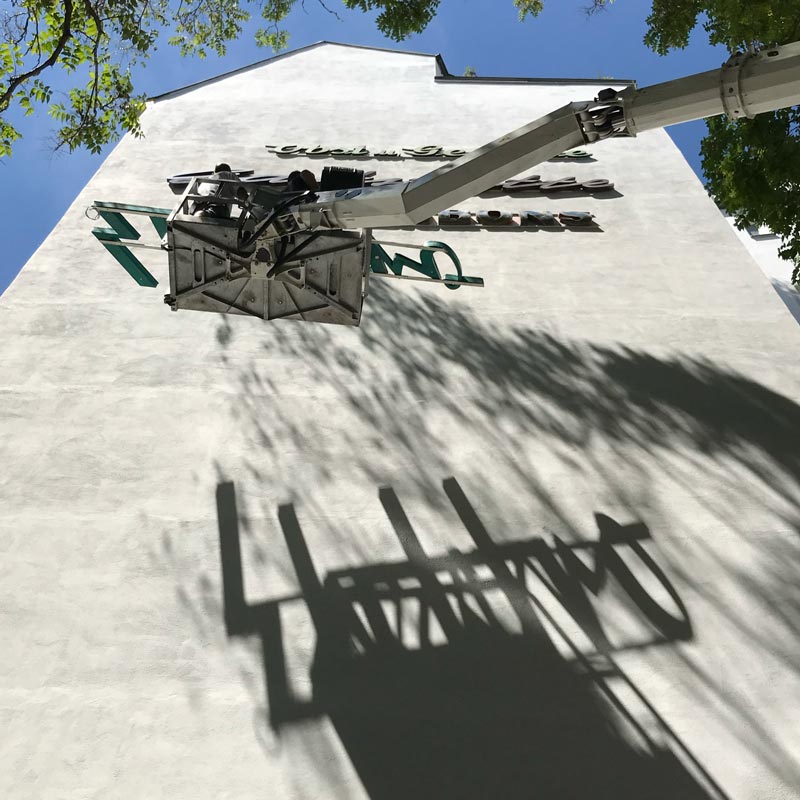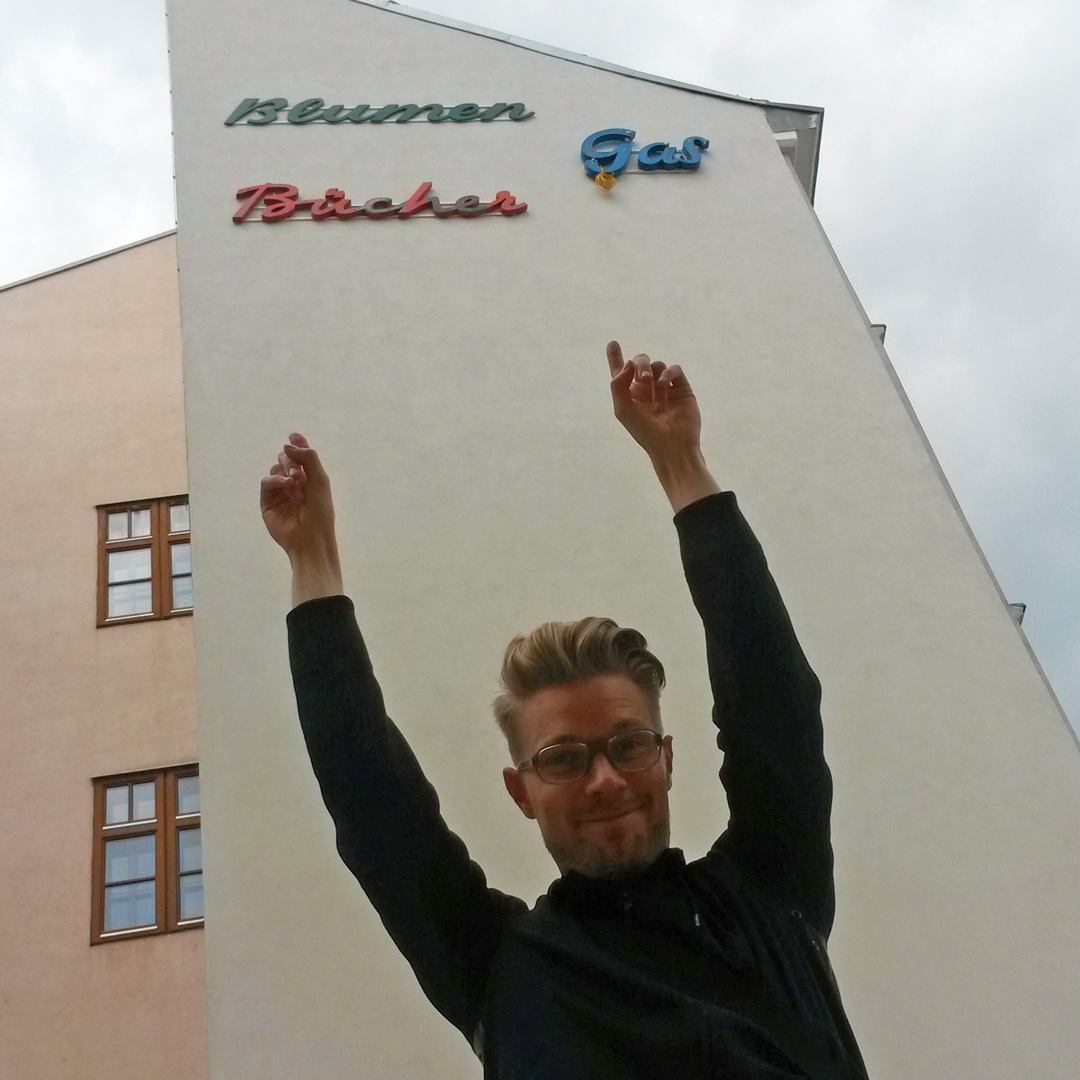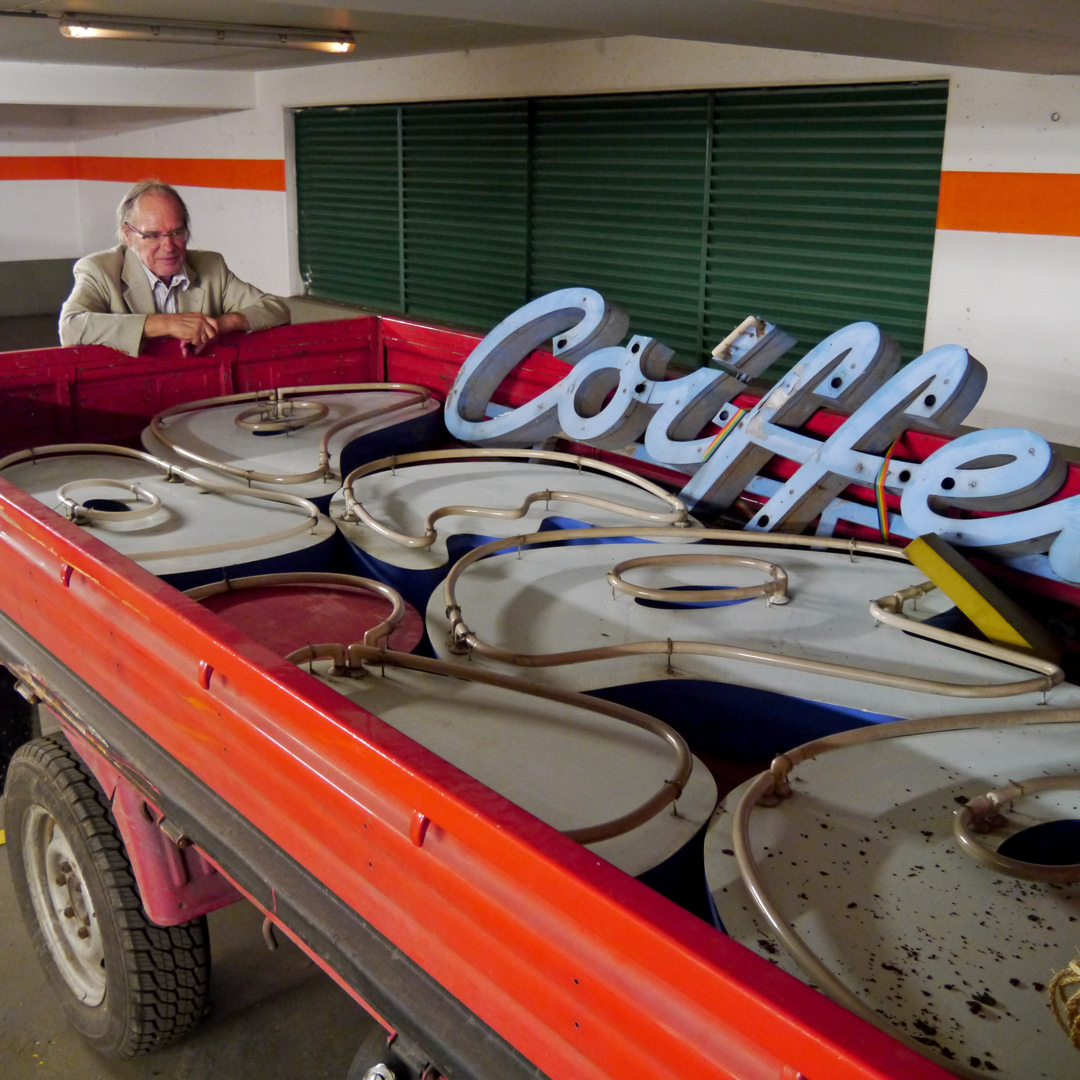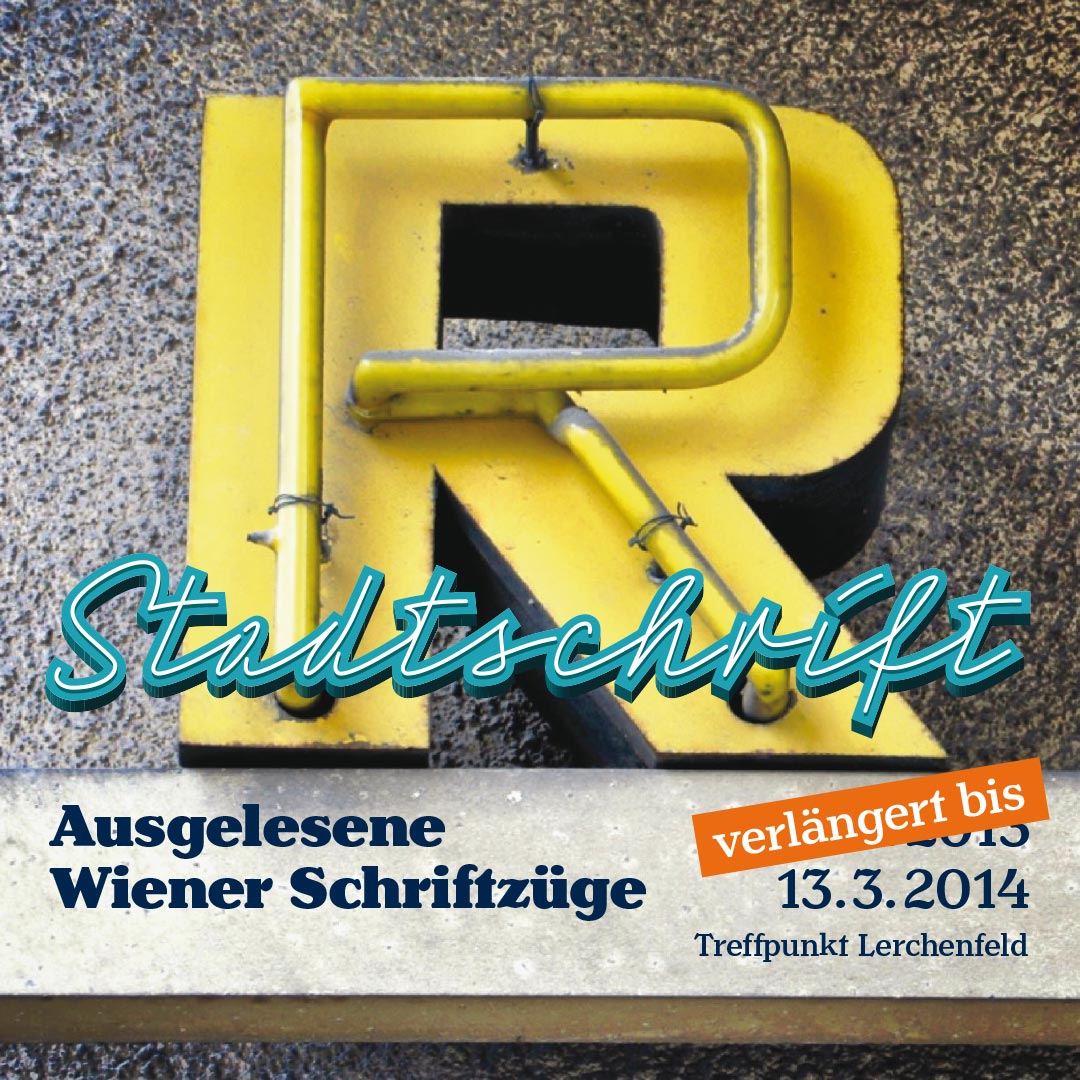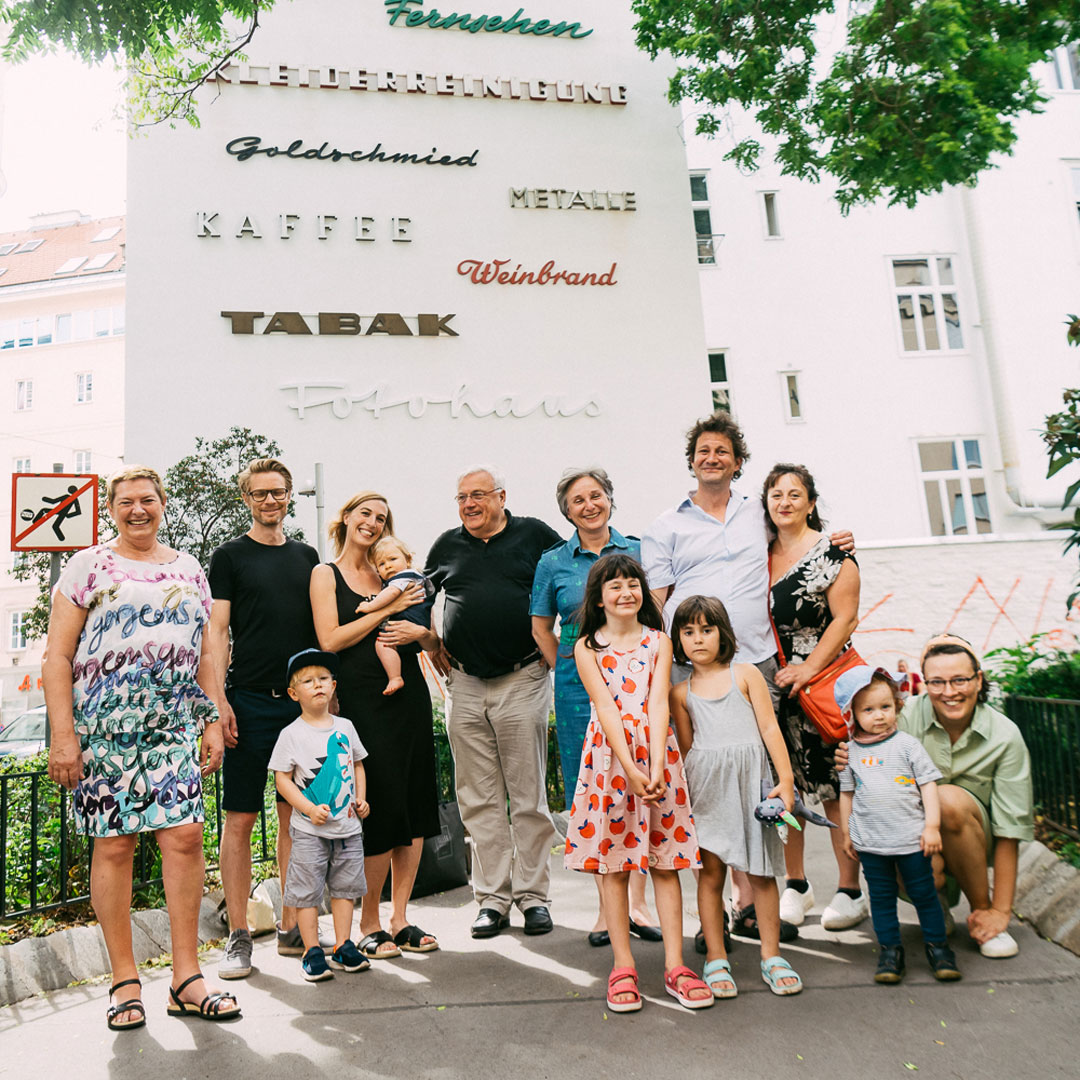
10 Jahre Stadtschrift!
Erste Abmontage, Vereinsgründung – Die ersten Buchstaben sind noch leichte Beute: bereits abmontiert in Schuttmulden und hinter Baustellenzäunen. Am 21. April 2012, vor genau zehn Jahren, stehen wir als frisch gegründeter Verein unserem ersten zu rettenden Schriftzug gegenüber.
Trotz komfortablem Gerüst beschäftigt uns die Abmontage ganze zwei Tage lang – vielleicht sind die Schrauben tatsächlich so festgerostet, wahrscheinlich aber ist es die noch fehlende Routine… Der 1964 gebaute Elektro Schriftzug aus der Hasnerstraße im 16. Bezirk ist jedenfalls bis heute eines unserer absoluten Lieblingsobjekte.
Ausstellung im Treffpunkt Lerchenfeld – Das restaurierte “Elektro” wird auch gleich zentrales Objekt unserer ersten Ausstellung. Vier Monate lang können wir in dem Lokal der “Lebendigen Lerchenfelderstraße” unsere noch junge Sammlung erstmals der Öffentlichkeit vorstellen. Die weit sichtbare Leuchtkraft hat wohl genauso ihren Anteil am unerwartet großen Publikumszuspruch wie der begleitende Artikel im Falter.
Mauerschau 1020 in der Kleinen Sperlgasse – Lange hatten wir nach einer Möglichkeit gesucht, die verlorenen Grätzelwahrzeichen wieder in die öffentliche Wahrnehmung zurückzuführen. Gemeinsam mit den jeweiligen Bezirksvorstehungen durchkämmten wir mehrere Bezirke nach geeigneten, gut sichtbaren Mauern.
Im 2. Bezirk werden wir endlich fündig, und wir können für vier Jahre die Baulücke neben dem Sperlgymnasium zur Zwischennutzung bekommen. Die lang verfolgte Idee der “Mauerschau” wird endlich Realität!
Schauraum – Als Stadtschrift Homebase und permanenten Ausstellungsort beziehen wir im März 2016 ein kleines Büro im 6. Bezirk. Dort stellen wir unsere Lieblingsobjekte aus, die für den Aussenbereich zu kostbar wären. Hier kann man sich einen Überblick über die technischen und gestalterischen Entwicklungen der Stadtbeschriftung verschaffen und sich durch unsere kleine feine thematische Bibliothek blättern.
Mauerschau 1060 in der Hofmühlgasse – Das inhaltliche Konzept einer “Frauennamenmauer” trugen wir beim Sammeln immer im Hinterkopf. Durch die überwältigende Unterstützung von 130 CrowdfunderInnen können wir es im September 2018 an die Wand bringen. Damit ist unsere Idee eines dezentralen typografischen Museum im öffentlichen Raum aufgegangen – vorerst nur für einen kurzen Moment, denn am Tag darauf müssen wir unsere erste Mauerschau 1020 wieder abbauen.
Mauerschau 1020 am Ludwig-Hirsch-Platz – Die Rückkehr der Mauerschau ins Karmeliterviertel. Zwei Jahre nach dem Abbau der ersten Mauerschau 1020 kommt die Mobilitätsagentur Wien mit einer AnrainerInneninitiative auf uns zu und bietet uns die Möglichkeit an, die freie Feuermauer am Ludwig-Hirsch-Platz für eine Folgeausstellung zu nutzen! Eine professionelle Montage kostet eine Stange Geld… wieder ist die große finanzielle Hilfe unserer UnterstützerInnen und der HauseigentümerInnen entscheidend für die Realisierung ♥.
Mauerschau 1230 im Carré Atzgersdorf – Der letzte Streich unserer 10 jährigen Vereinsgeschichte ist die Umsetzung unserer vierten Mauerschau. Mit Unterstützung des GB*Stadtteilmanagements und den örtlich tätigen Bauträgern wagen wir uns erstmals in einen Aussenbezirk und an eine Neubau-Wand – und es funktioniert! Durch den Kontrast aus Alt und Neu bekommt die Installation an diesem Ort eine besondere Wirkung.